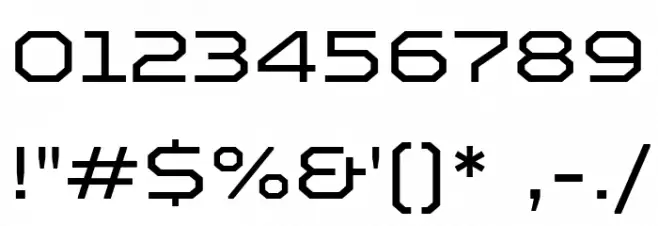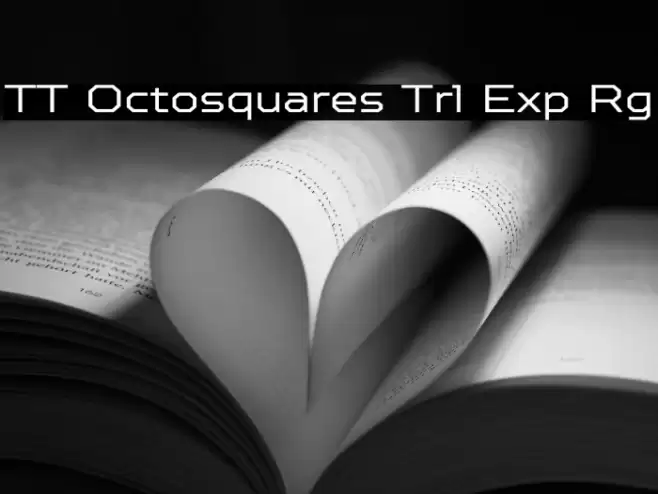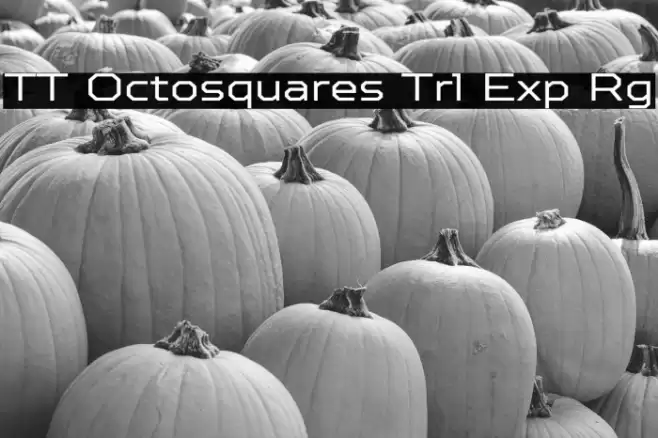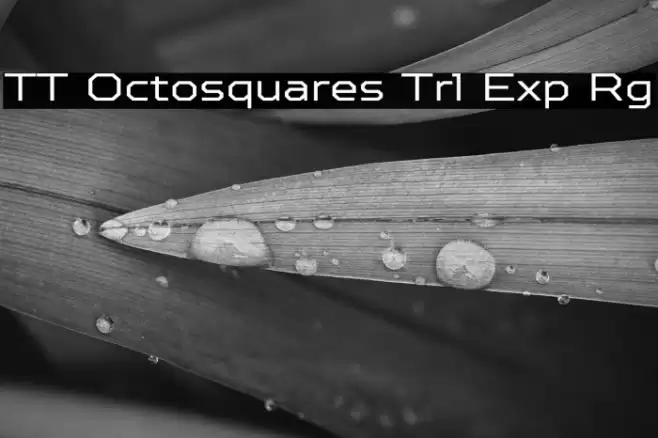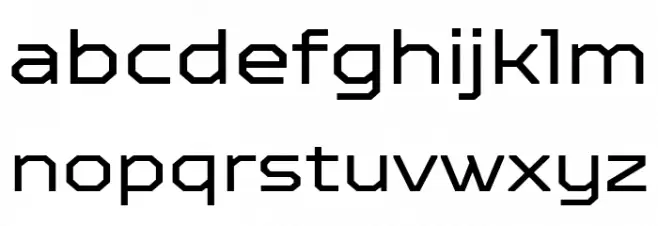
TT Octosquares Trl Exp Rg Font
| Nome | TT Octosquares Trl Exp Rg |
| Famiglia di caratteri | TT Octosquares Trl Exp |
| Style | TTOctosquaresTrlExp-Rg |
| Peso | Rg |
| Caso d'uso | Logos, Headlines, Digital Interfaces |
| Progetti proposti | Ideal for tech branding, modern posters, digital interfaces, and futuristic designs. |